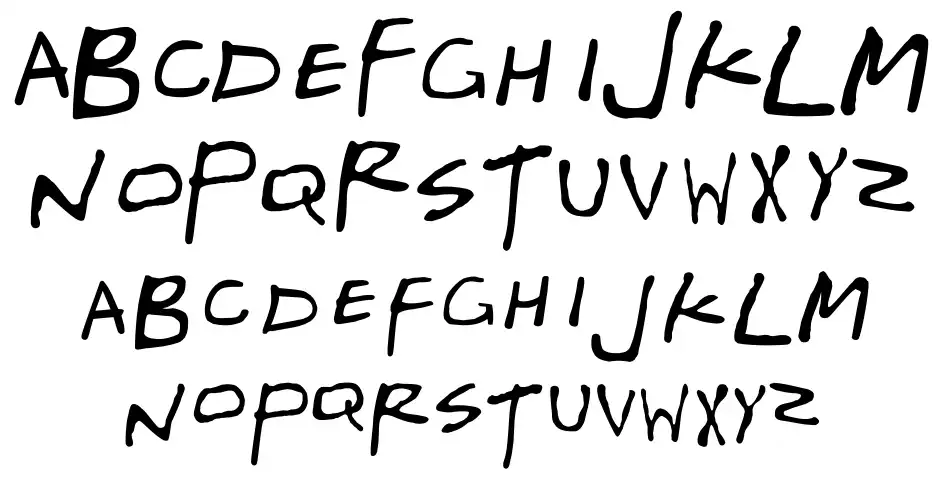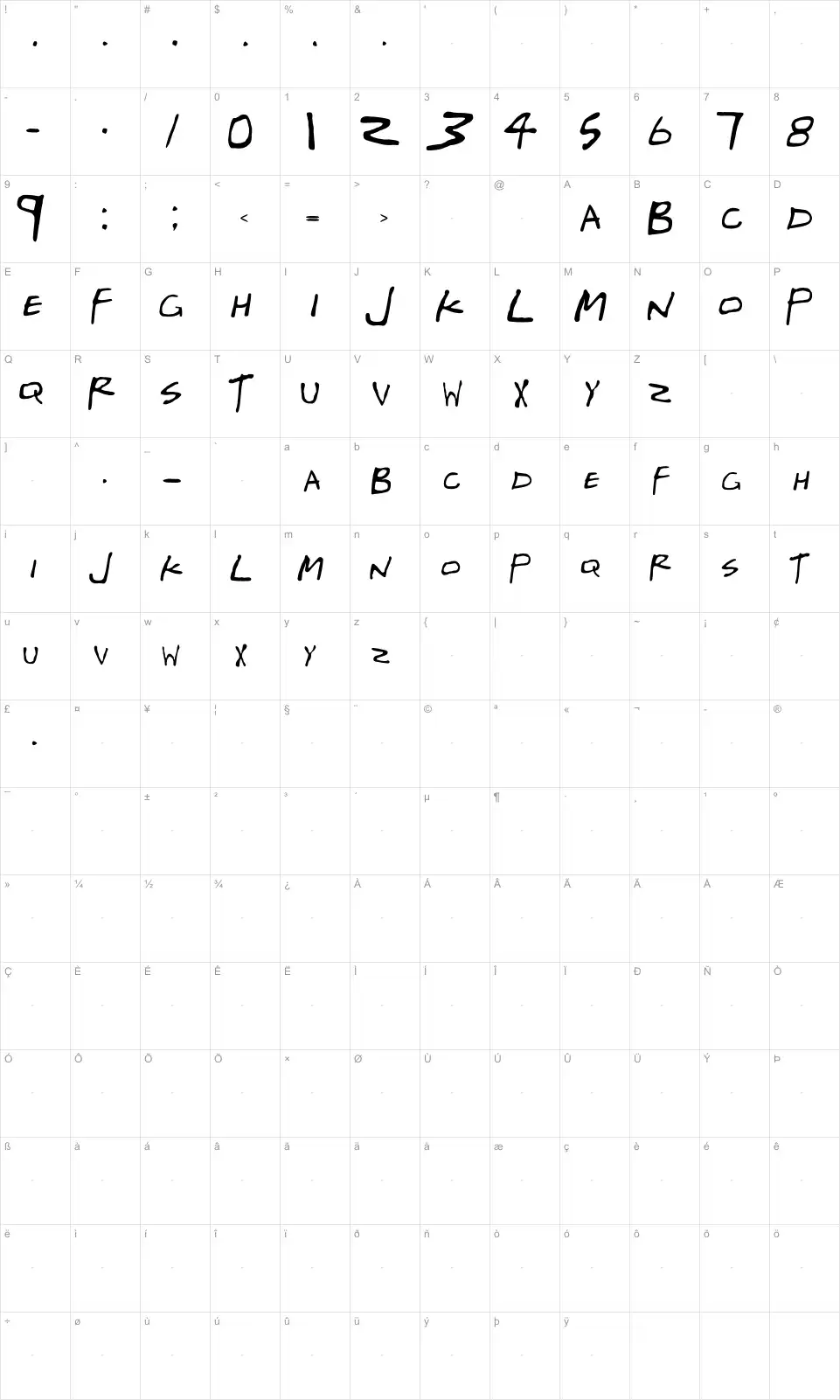
Gregor Miller’s Friends Font – Download Grátis
A fonte Gregor Miller’s Friends Font, categorizada como script e escrita a mão, oferece um estilo elegante e versátil para seu próximo projeto. Adaptada pela designer desconhecida, esta fonte é ideal para adicionar um toque criativo e único a sua publicação. Se você está à procura da melhor maneira de incorporar essa fonte à sua estética, o download é sua primeira opção. Não hesite em experimentar uma pré-visualização de texto personalizada para ter uma ideia clara do como a fonte se adaptará ao seu design antes de integrá-la no seu projeto. Com apenas 15 KB, o tamanho compacto da fonte garantirá que ela seja fácil de transportar e de carregar, sem prejudicar a qualidade do texto. Adicionada em 12 de julho de 2022, a fonte já é um sucesso entre os designers e criadores de conteúdo que buscam uma fonte de escrita a mão para dar um toque singular a suas publicações. Com 1931 downloads, é evidente que a font é apreciada e valorizada por sua elegância e facilidade de uso.